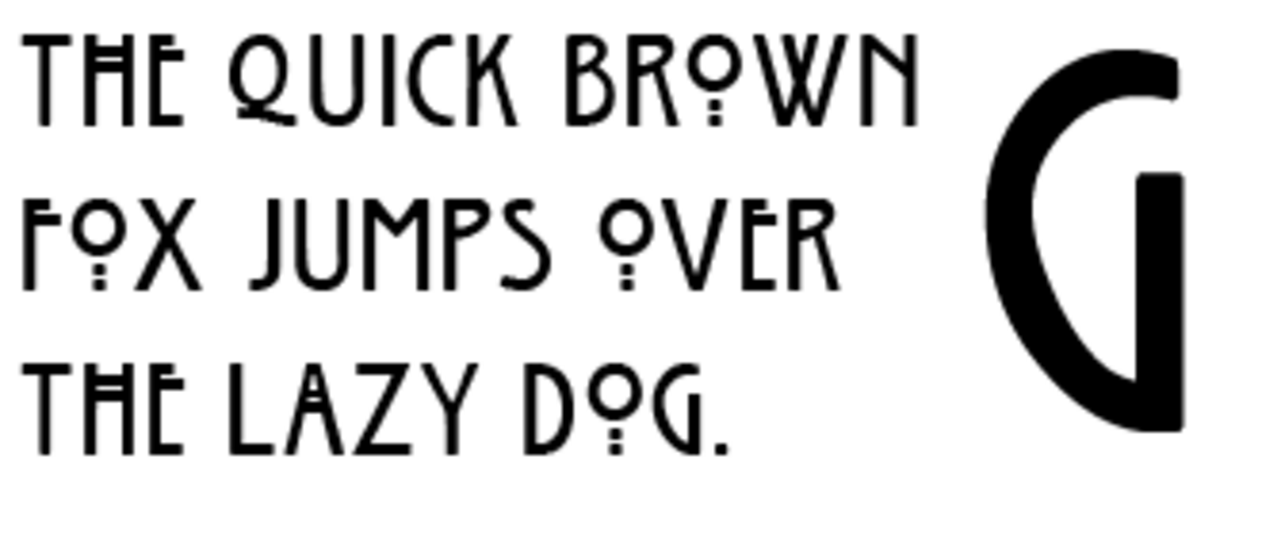
الصفصاف (خط)
Willow هو الاسم المشترك بين نوعين من الخطوط .
آي تي سي ويلو
| فئة | ديكوري |
| المصمم(ون) | توني فورستر |
| مسبك | مركز التجارة الدولية |
صُمم خط ITC Willow بواسطة توني فورستر في عام 1990. وعلى الرغم من كونه خطًا معاصرًا، إلا أن Willow يذكرنا بأسلوب الفنون والحرف الاسكتلندية الذي اشتهر به الرسام والمصلح الاجتماعي جيسي ماريون كينج (1875-1949)، والمهندس المعماري والمصمم تشارلز ريني ماكنتوش (1868-1928) من مدرسة غلاسكو . يعتمد الوجه على علامة لغرف شاي ويلو ، وهي واحدة من أربع غرف شاي في غلاسكو صممها ماكنتوش. يتميز الخط بالأشرطة المتقاطعة المزدوجة على الحرفين الكبيرين A و H ، والتصميم غير المعتاد للحرف الكبير O، والذي يرتفع فوق خط الأساس، مع نقطتين في المنتصف أسفل الوعاء.
الصفصاف العادي
| فئة | عرض |
| المصمم(ون) | جوي ريديك |
| مسبك | نوع أدوبي |
تم تصميم Willow Regular بواسطة Joy Redick في عام 1990، وهو جزء من مجموعة Adobe Originals Woodtype Collection.
يضم المسلسل التلفزيوني الأمريكي American Horror Story والمسلسل الفرعي American Horror Stories متغيرًا من ITC Willow* بشكل بارز في الحلقات بالإضافة إلى شعار المسلسل نفسه. [1] كان الخط المستخدم في الواقع نسخة معدلة قليلاً من خط Charles Rennie Mackintosh، والذي تم شراؤه خصيصًا لاستخدامه في العرض. يتميز هذا بحرف "O" معدّل ومسافة أحرف أقرب قليلاً من الأصل. كان استخدامه ملحوظًا بين هواة التلفزيون والأفلام لأنه لم يُنظر إليه أبدًا على أنه مرادف لنوع الرعب .
كما تم استخدام خط تشارلز ريني ماكنتوش في الفيلم السينمائي سبايدر مان 2. وقد ظهر في لافتة العرض لمسرحية برودواي (أوسكار وايلد "أهمية أن تكون جادًا") والتي ظهرت فيها ماري جين واتسون ( كيرستن دانست )، صديقة بيتر باركر المتقطعة. أمضى مخرج الفيلم، سام رايمي ، بعض الوقت في جلاسكو، اسكتلندا، في مدرسة جلاسكو للفنون، المعهد الذي التحق به (وأعاد تصميمه لاحقًا) تشارلز ريني ماكنتوش نفسه. أصبح رايمي من أشد المعجبين بعمل ماكنتوش وطلب على وجه التحديد استخدام هذا الخط في صنع اللافتات. [2]
تستخدم مدينة بيركلي، كاليفورنيا، خط ماكنتوش في شعارها واتصالاتها الرسمية. [3]